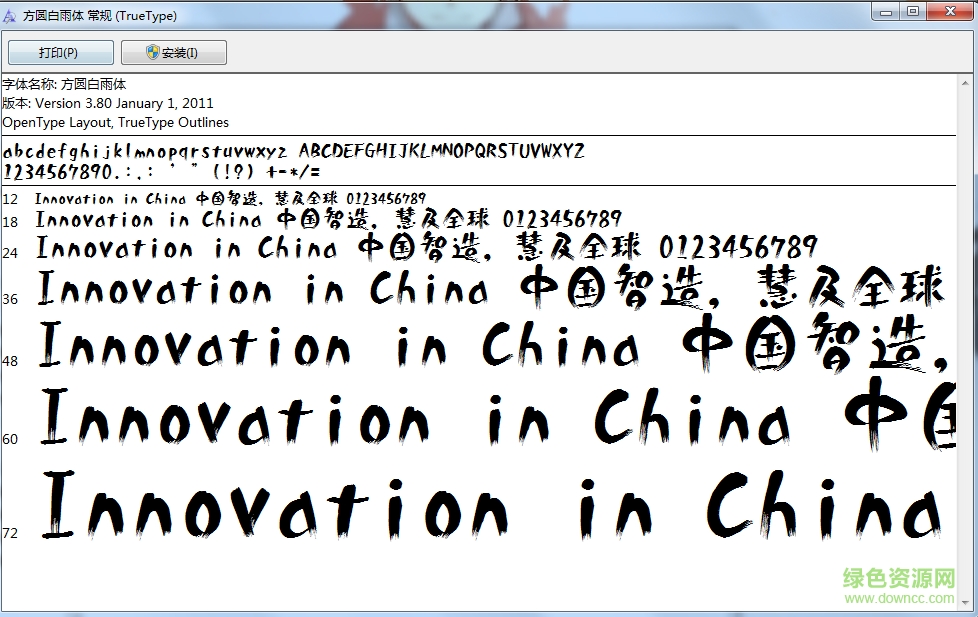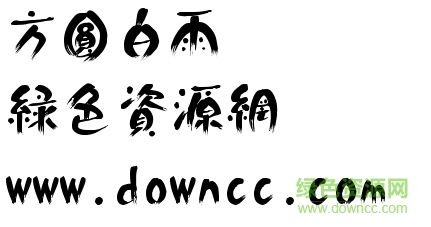
方圓白雨體繁體
方圓白雨體是一款水墨畫(huà)風(fēng)的繁體字體,清新大方的造型給人古風(fēng)韻味之感,喜歡的朋友歡迎來(lái)綠色資源網(wǎng)免費(fèi)嘗試!
方圓白雨體字體介紹
方圓白雨字體是一款書(shū)法藝術(shù)創(chuàng)意字體,本作品可用于出版印刷字體、廣告設(shè)計(jì)字體、網(wǎng)頁(yè)設(shè)計(jì)字體、包裝設(shè)計(jì)字體、 屏幕顯示字體等。